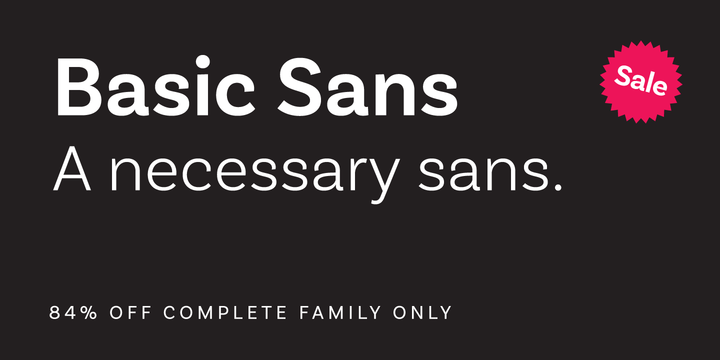
Passende Serifenlose zur Plantin
mein Notensatzprogramm (Sibelius) bietet verschiedene Fonts als Textschrift an. Ich nehme meistens Plantin MT (ansonsten werden Arial, Georgia und Times angeboten), die ich dann auch für die Titelei einsetze. Manchmal bräuchte ich aber doch eine Serifenlose und irgendwie bin ich mit keiner zufrieden...
Schon mal herzlichen Dank. Ich hatte zuerst an eine weiterlaufende Futura gedacht und die Avenir geht ja in diese Richtung.
Bei der Neutraface sitzt mir der horizontale Strich (bei A, E, ... hat diese Linie einen bestimmten Namen?) zu tief; ähnlich wie bei der Telefon. (Die beiden finde ich für sich großartig.)
Die Plan Grotesque wirkt für mich irgendwie zu verspielt (a, c, ...).
Dann schau mal nach der Neutraface 2.
Und diese?
• Gotham
• FF Mark
• Campton
• Galano Grotesque
• Scandia
Okay. Mir hat ihr Stil – insbesondere das ›a‹ und die x-Höhe – wieder gerade gut zur Plantin gefallen, wenn es harmonieren soll. Aber man kann ja auch genauso gut auf Kontrast setzen. Da bist Du mit einer geometrischen Sans wie im vorherigen Post schon gut beraten. Ich habe allerdings aus Deiner Frage noch nicht so recht rauslesen können, wofür Du die Sans einsetzen willst. Als Kombi zur Plantin (Textschrift?) oder als Ersatz oder …?
Ja... passt schon. Aber irgendwie stört mich, dass der untere Teil des a sich nach oben wölbt, wohingegen er bei der Plantin ansteigt.
Hach, ist das kompliziert...
Die Basic Sans ist gekauft und wird für das aktuelle Projekt wahrscheinlich genommen. Und dann suche ich in Ruhe weiter.
Ich freue mich also weiterhin über Vorschläge. :-)
Es war leider noch nicht der Aha-Effekt da und ich muss den Kram an diesem Wochenende erledigt haben...
Und dann werde ich mir alle Vorschläge noch einmal in Ruhe ansehen.
Ach quatsch, das war nicht böse gemeint! Ich habe doch auch gleich nachgelegt.:-)
Es wäre nur tatsächlich gut, wenn Du uns hilfst die Sache etwas einzugrenzen, denn im Grunde wurde meine Frage nach dem Konzept* noch nicht beantwortet. Ich glaube zur Plantin passen so viele, dass wir  Dir hier jetzt die halbe Myfonts-Sammlung aufzählen könnten ohne dass ein Aha-Effekt eintritt. Verstehst Du was ich meine?
… wenn es harmonieren soll. Aber man kann ja auch genauso gut auf Kontrast setzen. Da bist Du mit einer geometrischen Sans wie im vorherigen Post schon gut beraten. Ich habe allerdings aus Deiner Frage noch nicht so recht rauslesen können, wofür Du die Sans einsetzen willst.
Ich vermute Du willst einen Headline-Font, der eher im Kontrast zur Plantin steht und ein geometrisches Gerüst aufweist, richtig? Und diese Geometrische soll eher in Richtung Avenir (zweistöckiges a, nicht so scharfkantig) als in Richtung Futura gehen, ja? Und bei der Anwendung handelt es sich um reinen Notensatz für Print, oder?
Und welche Fonts hast Du Dir schon angesehen, die Dir nicht gefallen haben?
Sibelius ist ja nicht für seine typografischen Möglichkeiten bekannt, und die Wahl, die Plantin seit Version 7 beizugeben, passt für mich ins Bild. Sie fügt sich stilistisch eigentlich nicht gut ins Notenbild ein, dessen Formensprache ja im Wesentlichen aus dem 19. Jahrhundert stammt. Vielleicht ist es deshalb eine Überlegung wert, auch die Serifenschrift auf den Prüfstand zu stellen.
Ich mag für Notensatz die Hercules von František Štorm, die ich schon mit der Univers kombiniert habe (allerdings nicht für Noten). Eine etwas modernere Schrift, die stilistisch in dieselbe Richtung geht, ist die Harriet. Sie lässt sich mit der Alright Sans aus dem gleichen Hause kombinieren.
Anbei ein Beispiel. Es ist die Reinschrift eines Klavierauszugs von 1934. Abgesehen von den Dynamikbezeichnungen und der Taktangabe sind alle Textelemente aus der Plantin. Dabei sind die verschiedenen Größen und Schnitte vom Programm vorgegeben bzw. in der „Stilvorlage“ so festgelegt. Man kann die zwar alle Werte manuell anpassen (so wie ich auch die Größen der Titel-Elemente aus dem Original übernommen habe), ich würde diese Vorlage aber ungern ändern, da teilweise mehrere Bearbeiter an einem Werk arbeiten. Daher würde ich auch den Hauptfont ungern ändern.
Und jetzt gibt es Werke, bei denen der Komponist Anmerkungen macht (ähnlich der Anweisung in dem Kästchen). Oder wir als Herausgeber fügen zusätzliche Anmerkungen ein. Und dafür suche ich in erster Linie eine Serifenlose, die sich harmonisch einfügt, aber doch eindeutig als zugefügte Anmerkung erkennbar ist. Und die würde ich dann gerne auch im Vorwort und dem kritischen Bericht einsetzen.
@ Norbert P: In alten Notenausgaben der Edition Peters gibt es eine Serifenlose, die am Fuß der ersten Seite für den Firmennamen benutzt wurde. Ich habe schon ewig nach einer Schrift gesucht, die dem Original ähnlich sieht. Die Tenso trifft es erstaunlich gut. Vielen Dank für diesen Hinweis, auch wenn er gar nicht für mich gedacht war ...